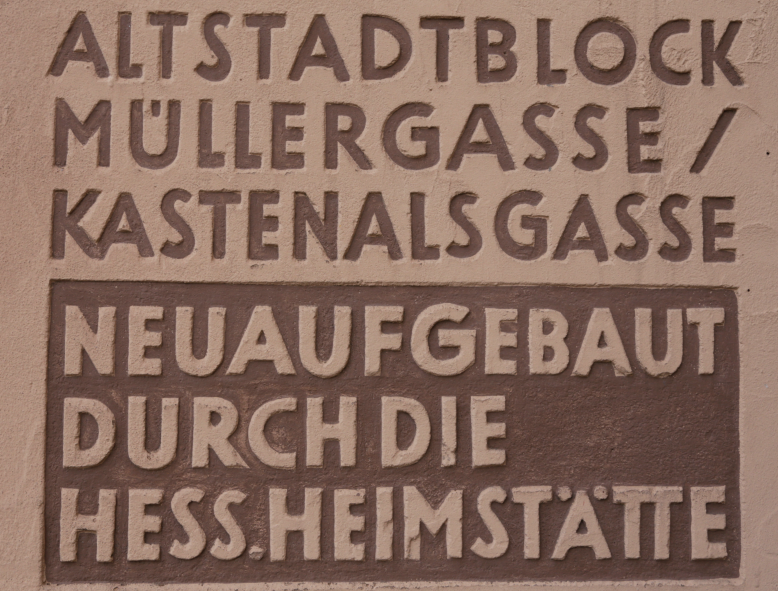
Suche Schrift dieses Fassadenreliefs aus den 50ern
Hallo liebes Forum, ich beschäftige mich zurzeit im Rahmen meines Designstudiums
mit einem Wohnviertel meiner Stadt und habe dort ein Relief entdeckt, welches aus den 50ern
stammt. Ich suche diese oder eine ähnliche Schrift. Darf auch was kosten. Vielleicht kann mir jemand von euch
Dass es diese Schrift genau so als Satzschrift nicht gibt, ist klar, oder? Ist halt handgemacht; alle Buchstaben unterscheiden sich.
Was am nächsten kommt? Eine geometrische Serifenlose, aber mit Titelsatzumlauten und in Abgrenzung von der Futura mit geradem M und G mit Extra-Knick. Da gibt’s gestimmt was …
was eventuell auch helfen könnte wäre ein Steinmetzer für Grabsteine, der schon im 20 jahrhundert gearbeitet hat. In der Tat die Buchstaben werden wenns nicht passt sogar kleiner.  Steinmetz ist kein Typograf so wie ein Maurer kein Architekt ist ;-)
Na ja, zumindest eben schon ein "Bedarfs-Typograf" eben angepasst an sein Material. Und nicht selten liefern sie die Vorlage für großartige Schriften, sei es die römische Kapitalis, sei Hermann Zapfs Optima, der ja hierfür 1000 Lire "opferte"
Ja Peter ich will ja keines wegs die steinmetzgilde schlecht machen. Aber selbst ich bin typografisch nicht so gefestigt. Wenn man jetzt mal das  Wort Bedarfstypograf an hand eines schlechten Beispieles  zeigen müsste wäre das hier mein erster kandidat